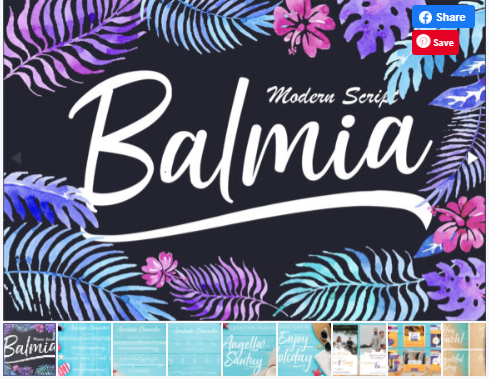
Balmia Font
Balmia - это романтичный и плавный каллиграфический шрифт с персонажами, танцующими вдоль базовой линии. Он придаст изюминку любому дизайнерскому проекту, который вы желаете создать! Этот шрифт имеет кодировку PUA, что означает, что вы можете легко получить доступ ко всем удивительным глифам и лигатурам!